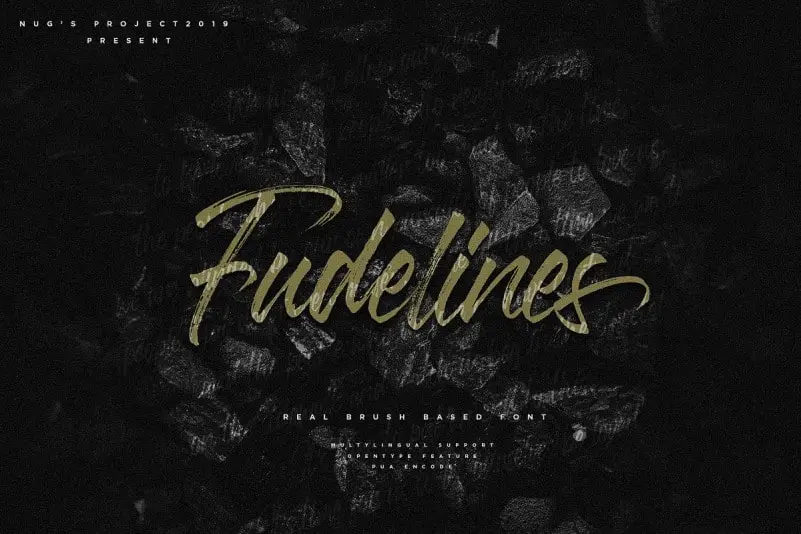
Fudelines Brush Font – Download Grátis
A Fudelines Brush Font é uma tipografia moderna que oferece uma sensação única para seus projetos digitais ou impressos. Este tipo esculpido com pernas de pau tem traços contínuos, proporcionando um resultado elegante e versátil. É ideal para aplicar em designs diversos como estampas de lençóis de cama, t-shirts customizadas, miniaturas de vídeos ou qualquer outro projeto que exija uma aparência única e sofisticada. Com sua configuração fluida e natural, a Fudelines Brush Font não apenas enriquece os seus projetos de design impressos ou digitais, mas também ajuda em criações mais expressivas para o mundo da moda, onde cada detalhe conta. Este tipo especializado na tipografia é uma escolha perfeita para aqueles que buscam um estilo autêntico e único para suas produções.